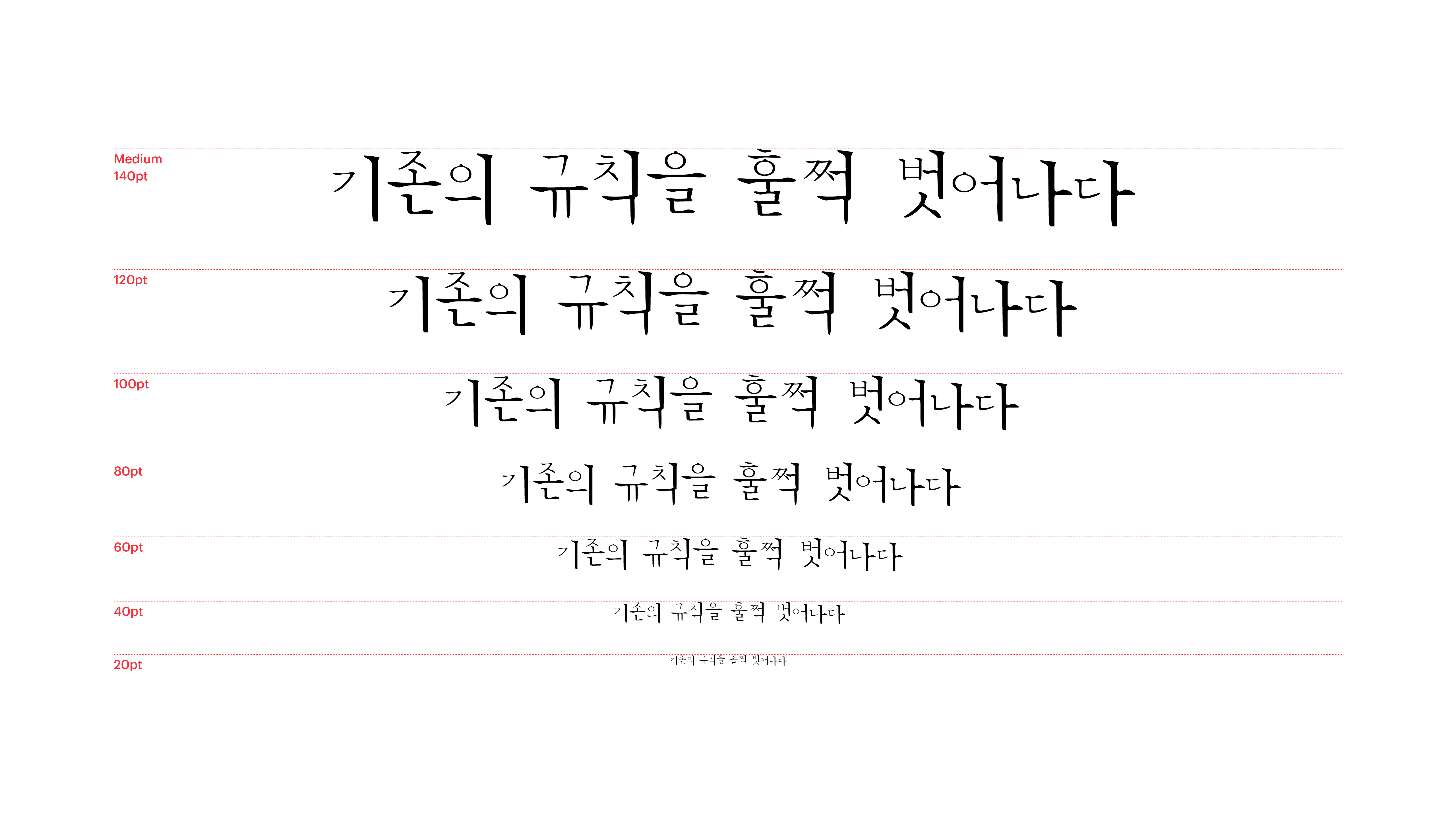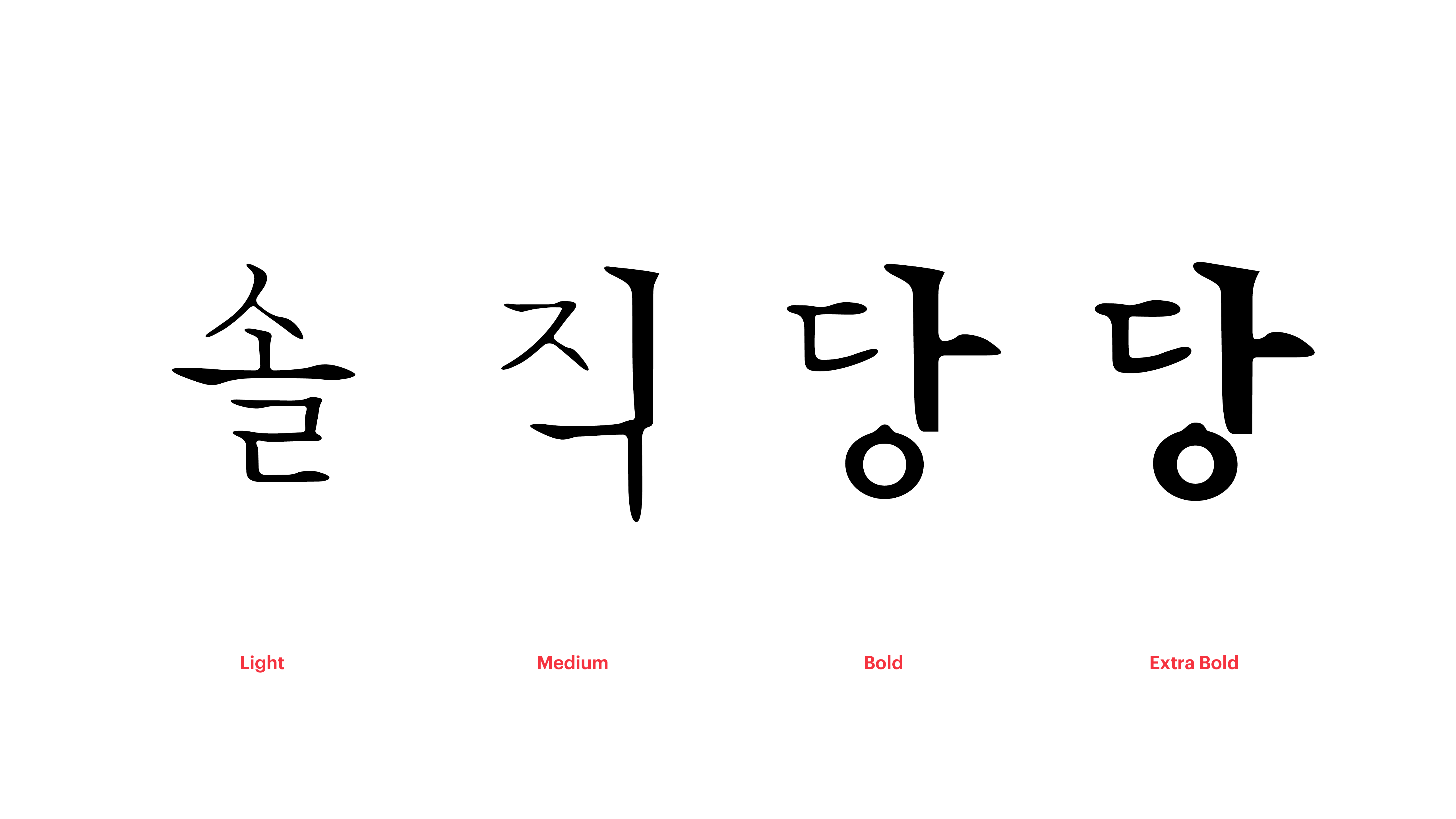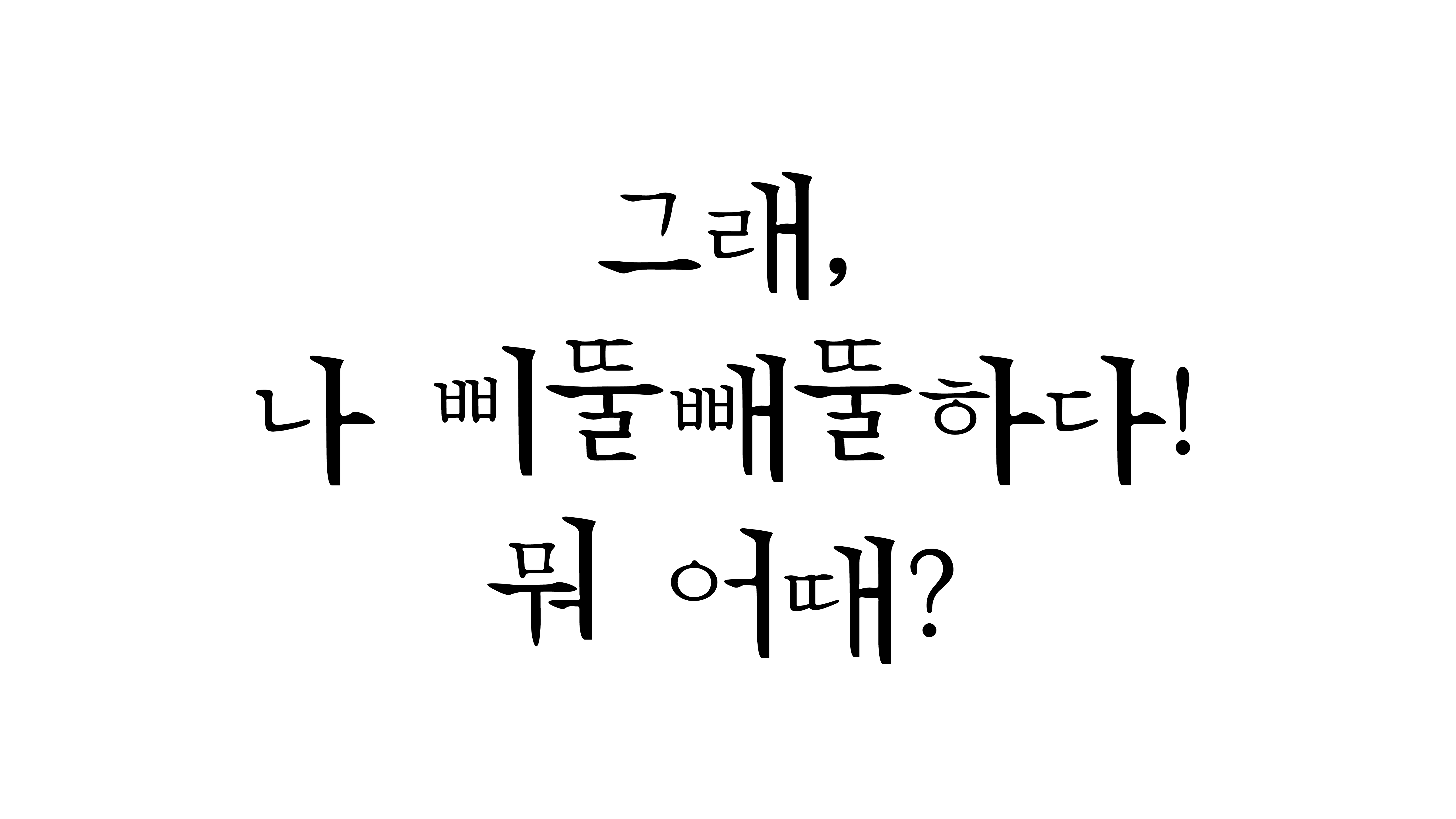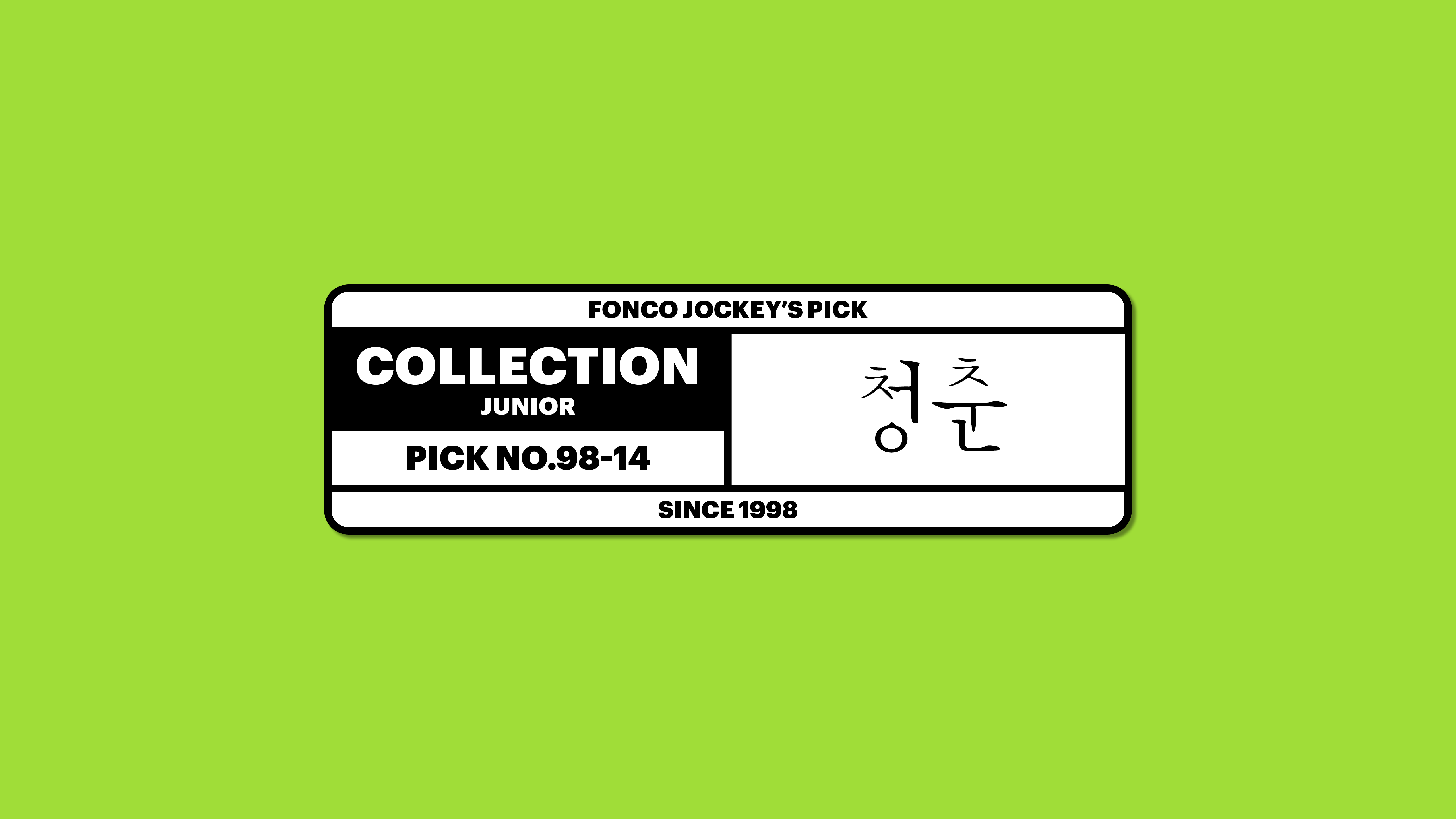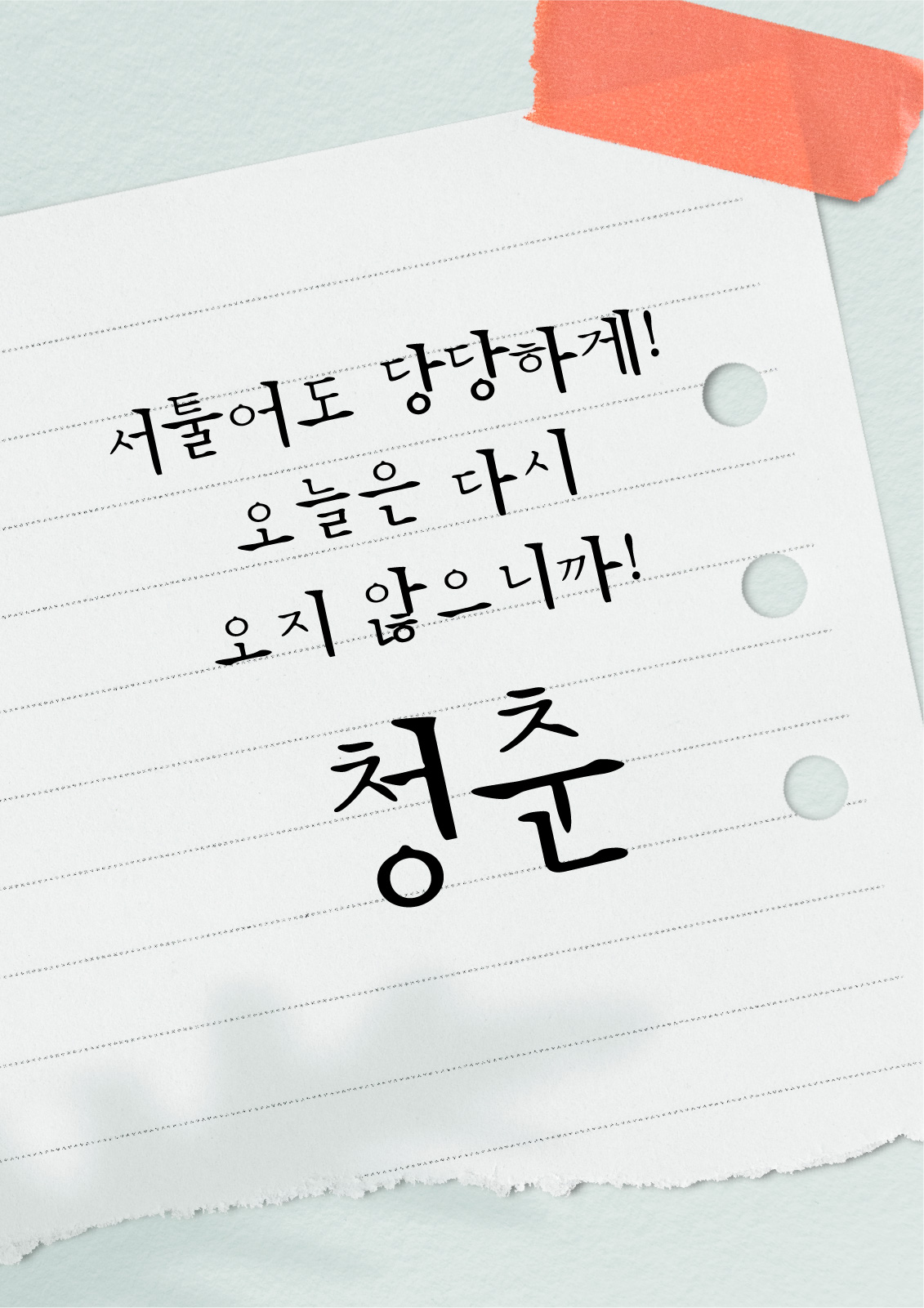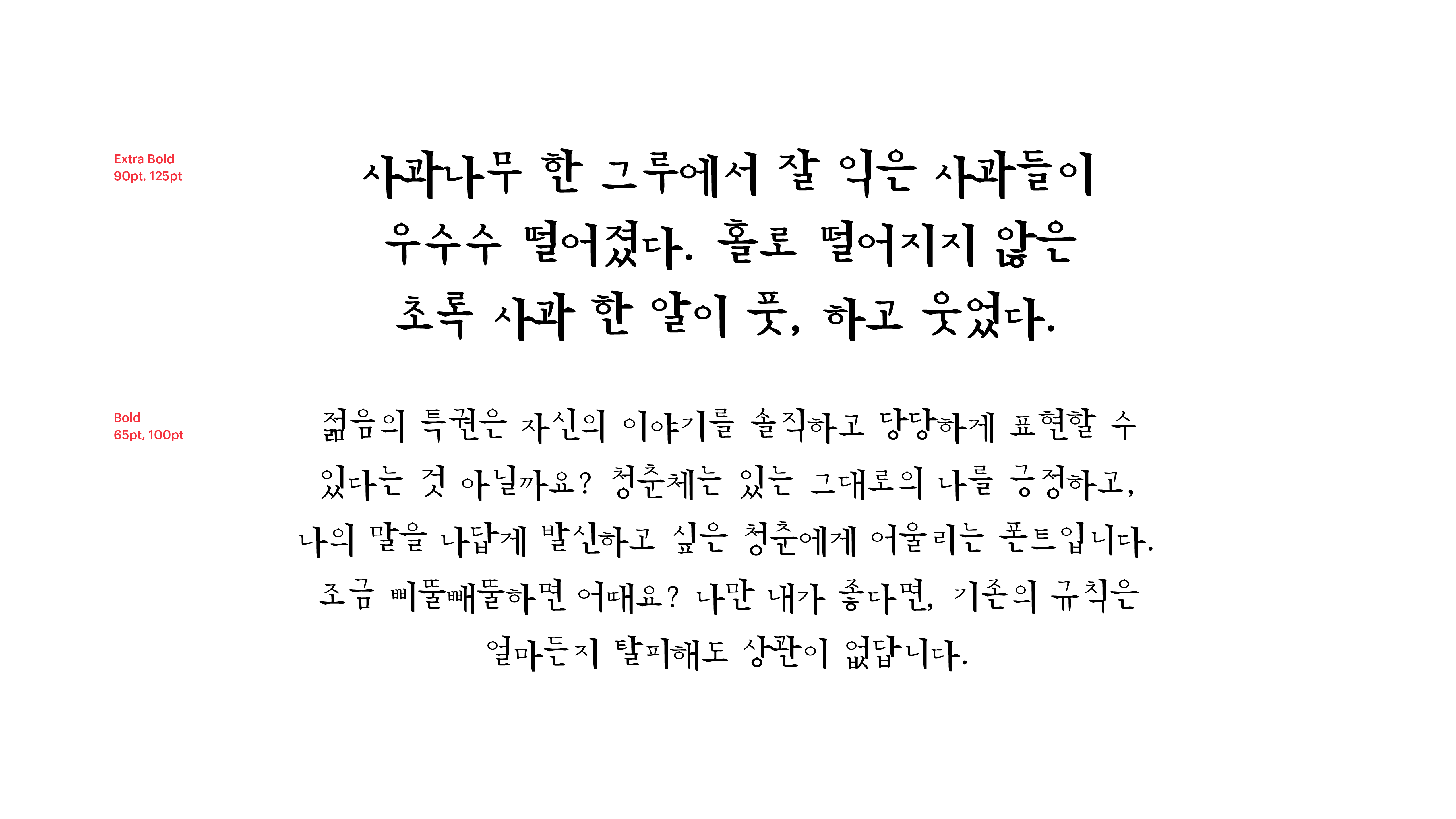
청춘
Yoon 청춘
젊음의 특권은 자신의 이야기를 솔직하고 당당하게 표현할 수 있다는 것 아닐까요? 청춘체는 있는 그대로의 나를 긍정하고, 나의 말을 나답게 발신하고 싶은 청춘에게 어울리는 폰트입니다. 조금 삐뚤빼뚤하면 어때요? 나만 내가 좋다면, 기존의 규칙은 얼마든지 탈피해도 상관이 없답니다.